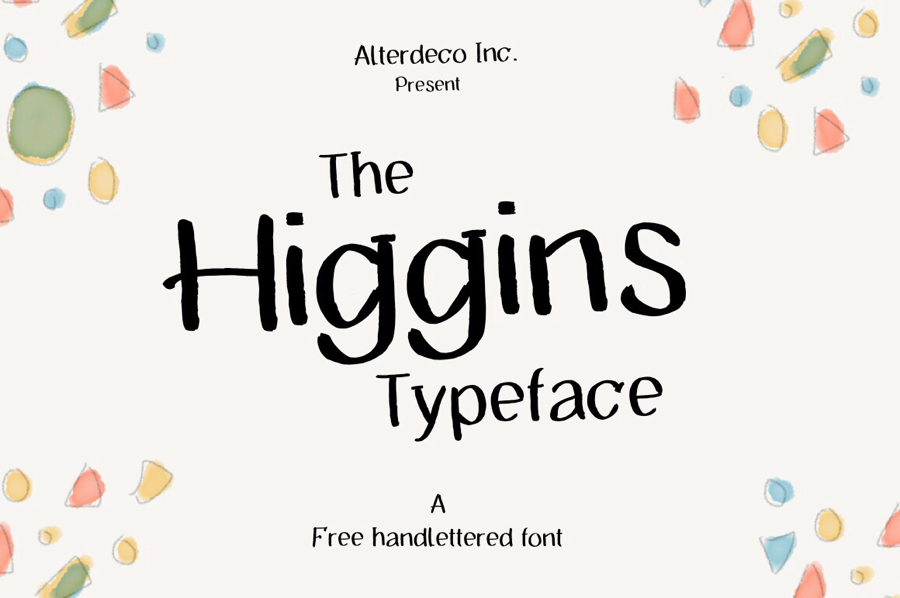
A The Higgins Typeface é uma fonte de escrita manuscrita livre que Hamilton criou com carinho. Esta fonte gratuita tem uma perfeição imperfeita que faz dela a escolha perfeita para dar um toque pessoal a tudo o que você está trabalhando em. Com seu charme único e sua capacidade de trazer personalidade a qualquer projeto, é óbvio porque esta fonte foi projetada para se adaptar a várias necessidades digitais, especialmente nas categorias onde a escrita manuscrita faz uma diferença significativa. Seja você um designer gráfico ou editor de conteúdo digital, The Higgins Typeface oferece uma maneira divertida e criativa de personalizar seus materiais com uma fonte que transmite sua identidade única.